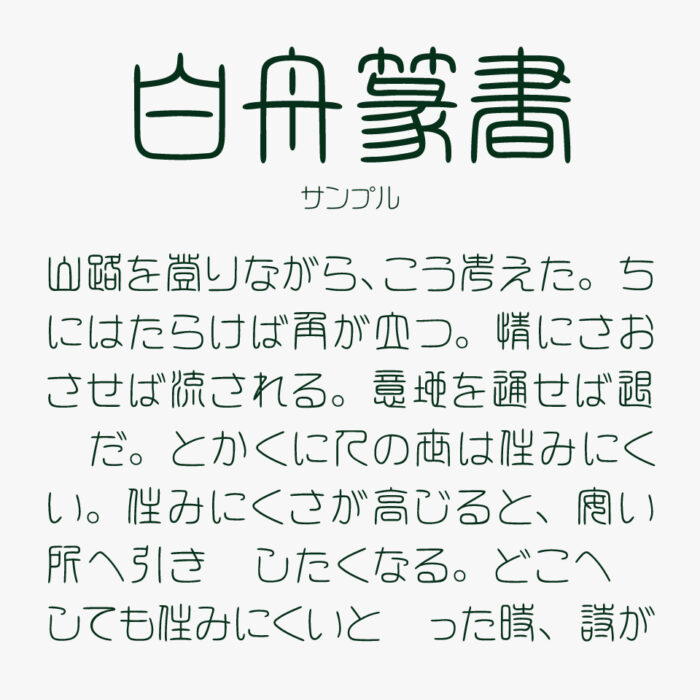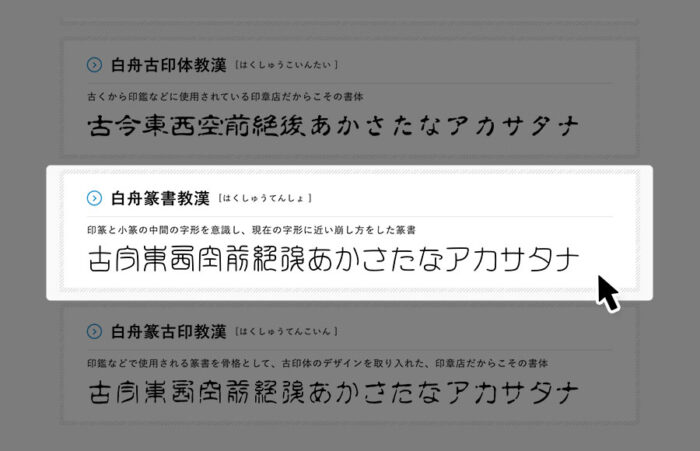
白舟篆書フォントは、古代中国の「篆書体(てんしょたい)」をベースにした装飾的で古風でユニークなフォントです。
文字の一画一画が丁寧に線対称で構成されており、印篆と小篆の中間の字形を意識してますが、現代版として再構築され制作されているので、使いやすく読みやすくなっています。
マンガ「呪術廻戦」のロゴでも篆書体がもちいられていたので、馴染があるかも多いと思います。